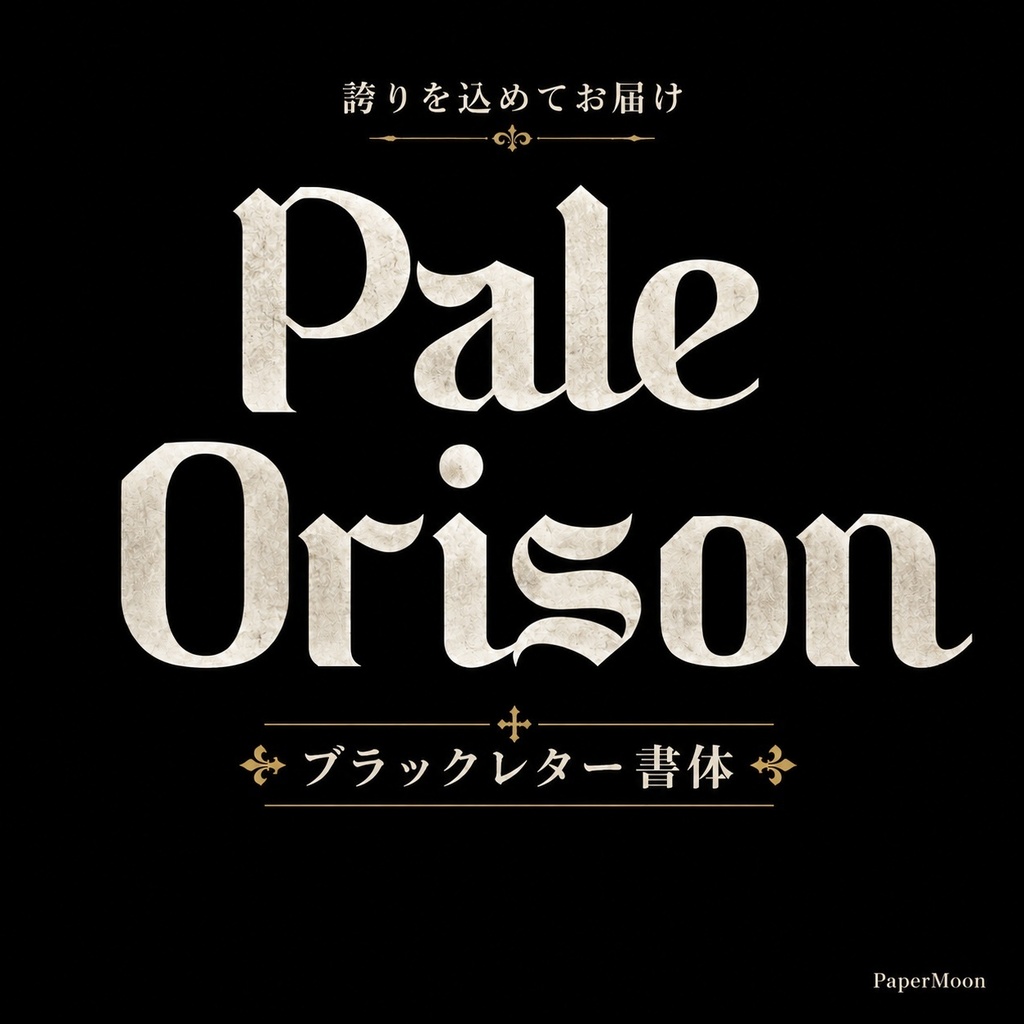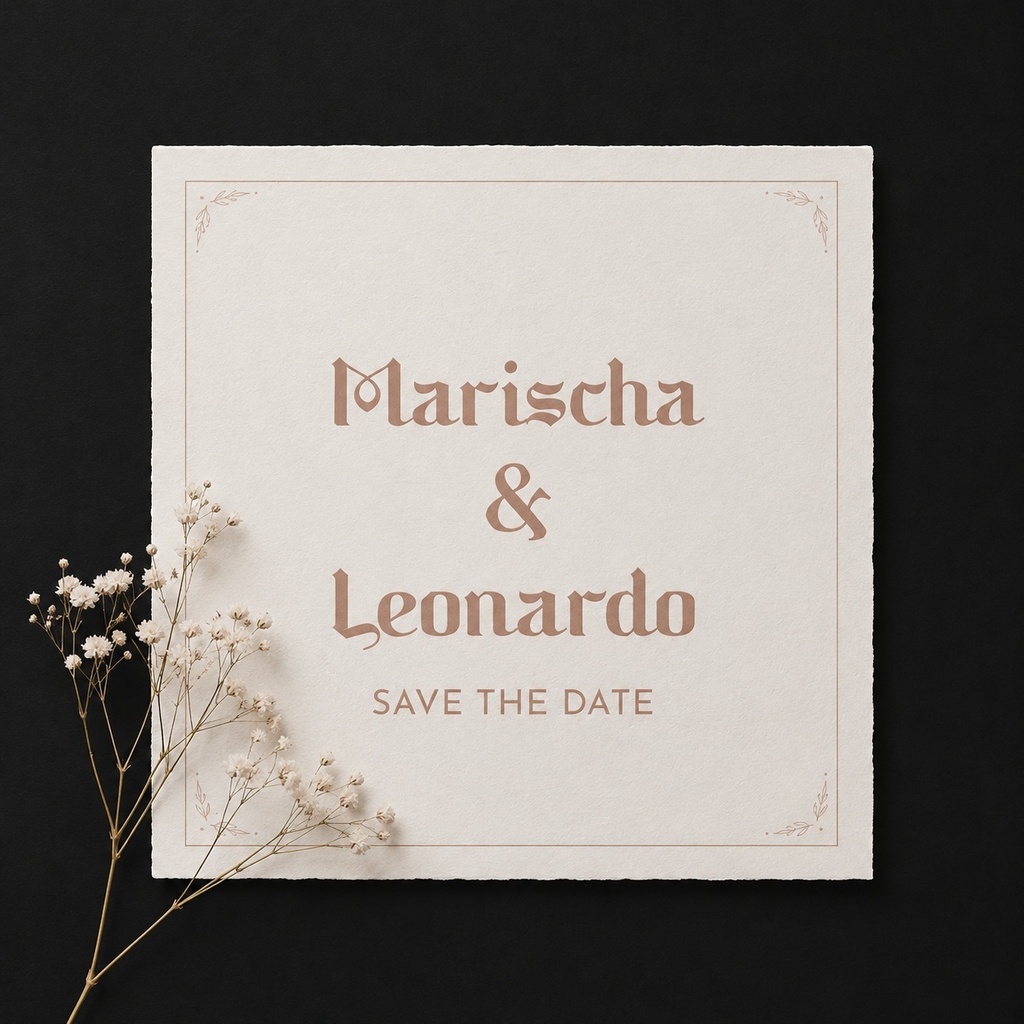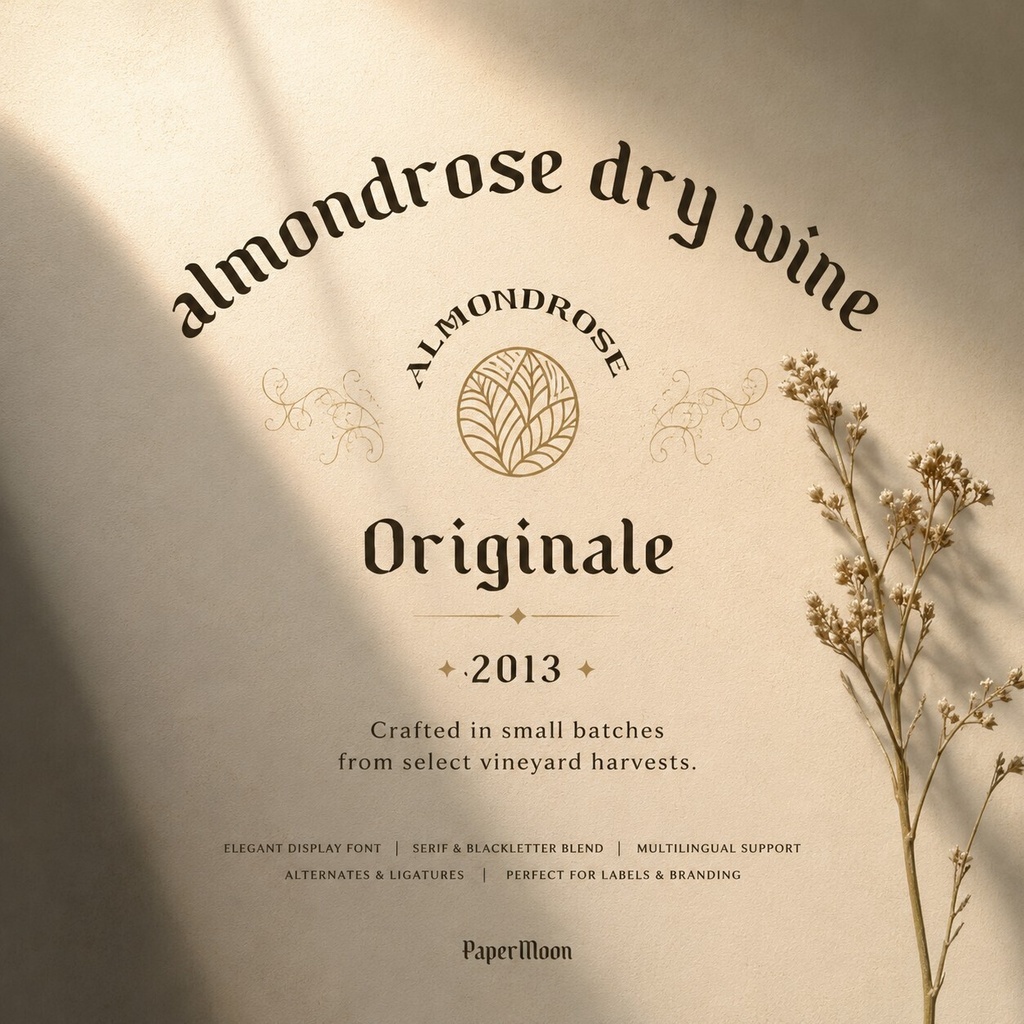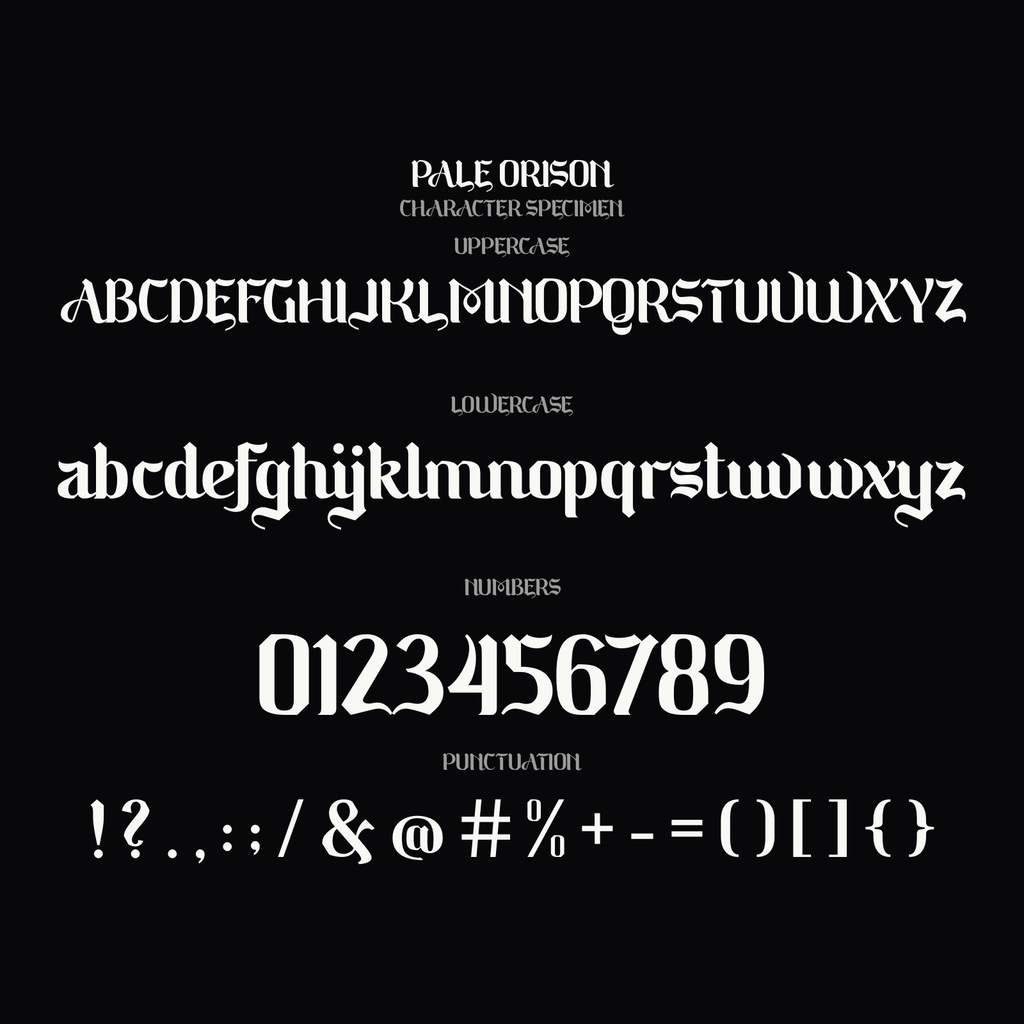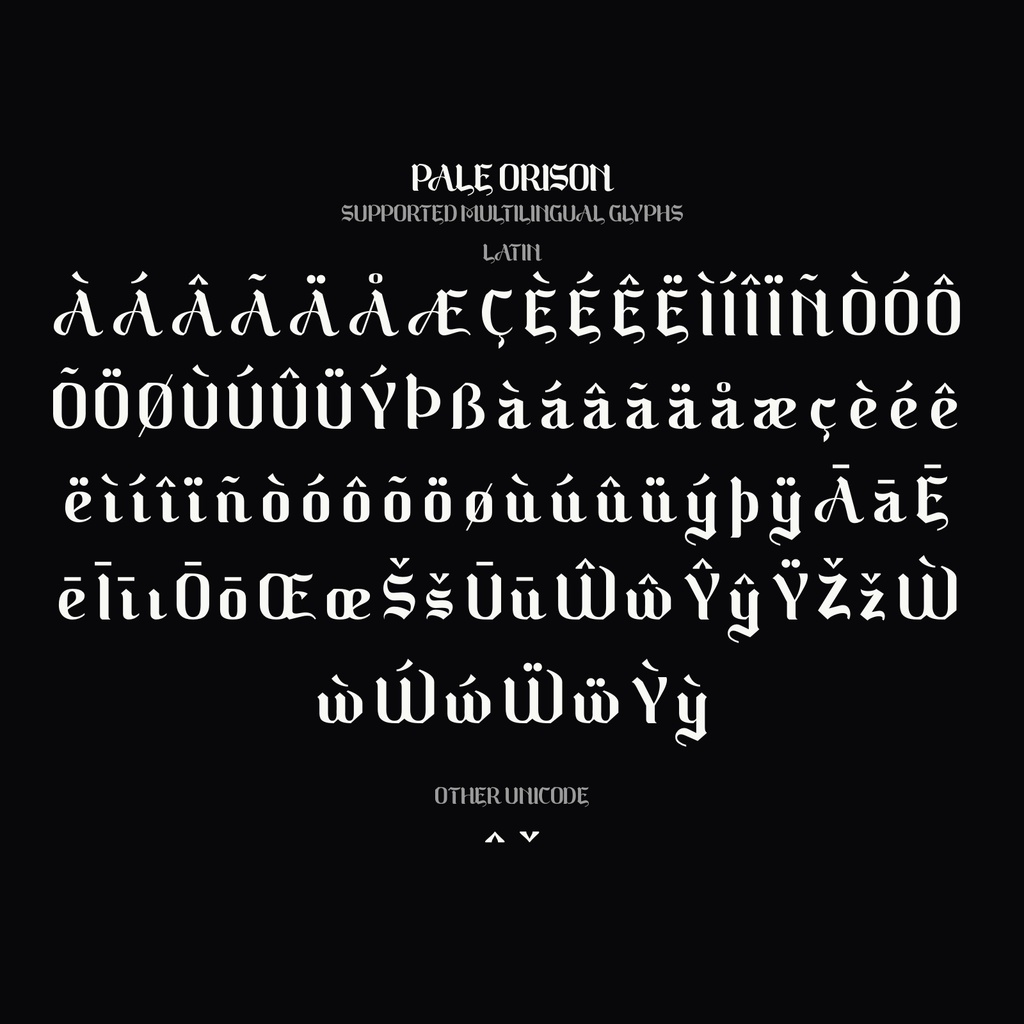
Pale Orison | 重厚なブラックレター欧文フォント | ロゴ・パッケージ・ウエディング向け
重厚で格式あるブラックレターで、ロゴ、パッケージ、ウエディングからテロップ・サムネイルまで、存在感のある文字を表現できる欧文ディスプレイフォントです。中世ゴシック建築とゴシック美術から着想を得た力強いラインと鋭い角、精緻なディテール、装飾的なフローリッシュが、文字に威厳と高級感を与え、商用利用可能・ロイヤリティフリーで安心してご利用いただけます。 Pale Orisonは、時代を超えて受け継がれるゴシック美術と中世ゴシック建築から着想を得た、太く重厚なブラックレターの欧文ディスプレイフォントです。力強いライン、鋭い角、精緻なディテール、尖頭アーチを思わせる造形、ドラマチックなセリフと装飾的なフローリッシュが、文字に威厳と高級感を与えます。 美しく個性的な合字と代替文字を組み合わせることで、印象的なロゴや見出しから、エレガントで格式あるウェディングデザインまで、多彩な文字表現を楽しめます。ブランディング、広告、ラベル、商品パッケージ、写真作品、透かし、招待状、ステーショナリー、SNS投稿など、存在感のあるタイポグラフィが必要な制作におすすめです。 収録内容 ・大文字 ・小文字 ・句読点 ・合字 ・代替文字 ・記号 対応文字 ・英字の大文字・小文字、句読点、記号 ・日本語文字の収録情報は提供されていません 用途 ・ブランドロゴ、ワードマーク、ブランディング ・広告、SNS投稿、写真作品、透かし ・ラベル、商品パッケージ ・ウェディングデザイン、招待状、ステーショナリー ・見出しやタイトル、YouTubeのテロップ・サムネイルを中心とした装飾的な文字組み 形式 ・OTF ・TTF ・WOFF ・WOFF2 対応環境 ・各形式に対応した環境で使用するフォントデータです ・具体的なアプリケーションや対応OSの情報は提供されていません 利用許諾 ・商用利用と個人利用の2種類のバリアントを用意しています ・商用利用版はロゴ、ブランディング、広告、商品パッケージなど商用・収益化作品にご利用いただけます ・個人利用版は購入者ご自身の非商用プロジェクト、学習、練習、個人制作にご利用いただけます ・各バリアントの正式な利用範囲、禁止事項、フォントデータの取り扱いは販売時に設定する利用規約に従ってください